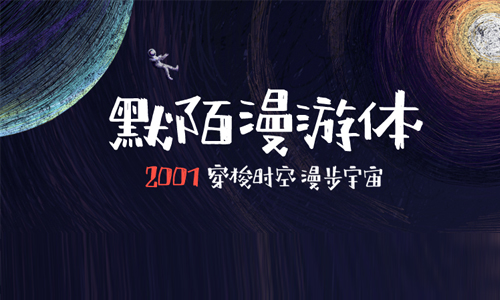
默陌漫游體字體是一款可愛(ài)趣味風(fēng)的手寫風(fēng)格的字體,采用橫劃為細(xì)、豎劃為粗的書寫規(guī)則,強(qiáng)化筆畫的粗細(xì)對(duì)比,筆畫邊緣和肌理保留大量手寫涂繪的質(zhì)感,豐富了字體細(xì)節(jié)。字體角度各異,呈現(xiàn)出自由晃動(dòng)的形態(tài),賦予字體活潑靈動(dòng)的個(gè)性色彩,適用于海報(bào)廣告、影視媒介和插畫配字等多種用途。歡迎喜歡默陌漫游體的朋友前來(lái)下載使用。